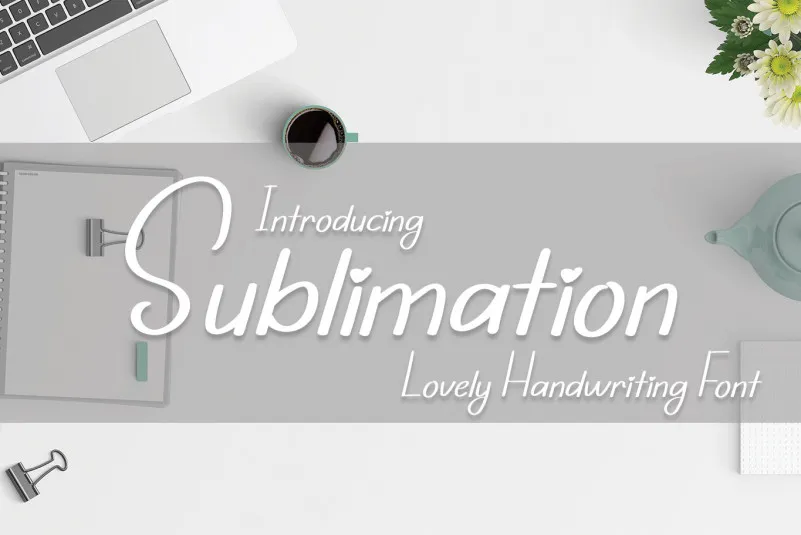
Sublimation Script Font é uma elegante escolha para quem busca um estilo delicado e único no seu design. Escrevendo a mão com um traço fininho, esta fonte captura momentos de criatividade simples mas poderosos, capaz de fazer sua obra se destacar e capturar o interesse do público. Ideal tanto para criações individuais quanto para projetos que exigem uma personalização única, Sublimation Script Font é a fonte perfeita para aqueles que procuram uma escrita autêntica e envolvente em seus trabalhos. Com seu designer experiente Erik Studio, você pode confiar na qualidade e no design único desta fonte, tornando-a o ponto final perfeito para qualquer projeto de design.